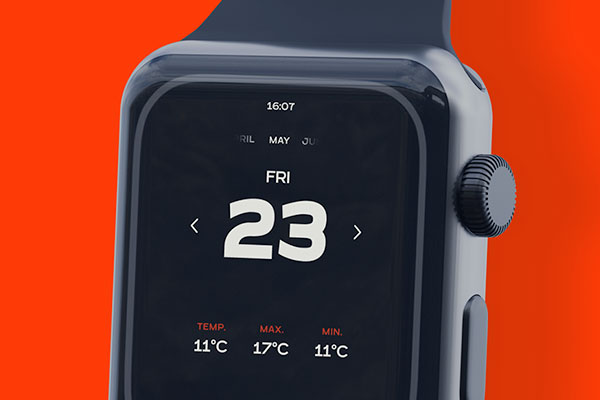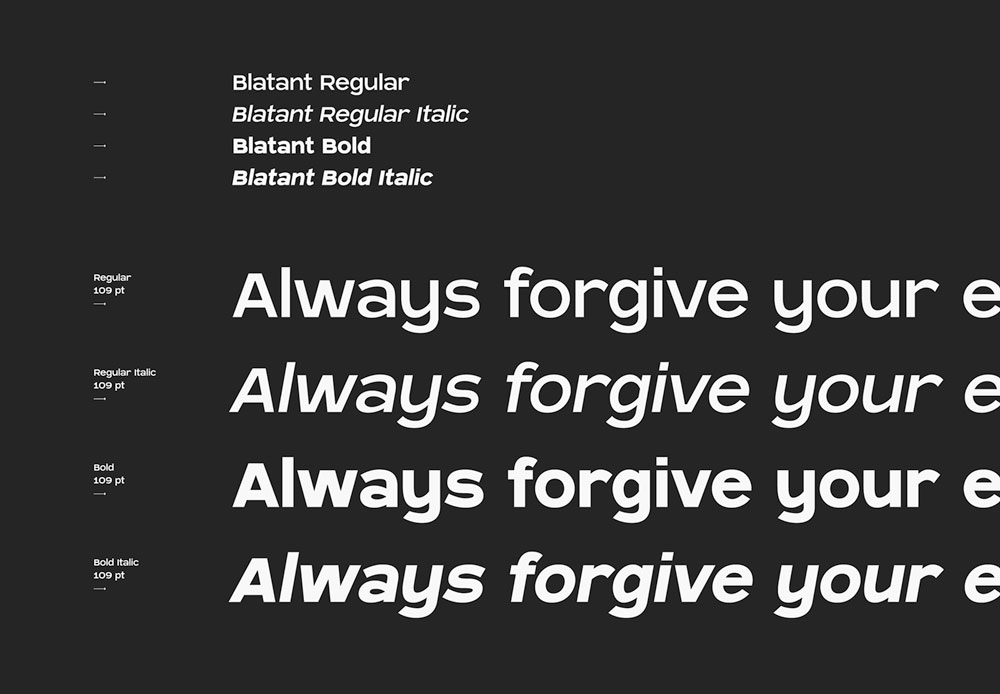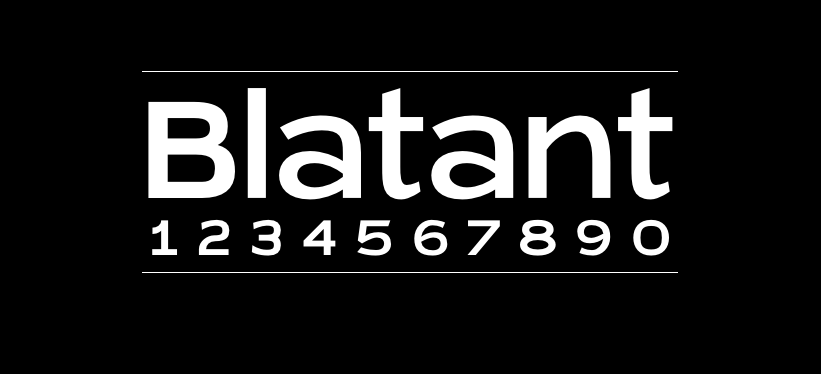
Blatant
Blatant字体介绍
Blatant是阿根廷的设计师Tomás Castiglioni创作的一款优秀的英文字体,该字体通用性较强,笔画较粗比较稳重,旨在引起人们的注意,以使它在任何视觉作品中都不会被忽视。它的区别在于其广泛的替代性高框标牌集。
该字体包含4种不同粗细和斜体,自由字体已在下方提供预览图。
Blatant字体应用示例